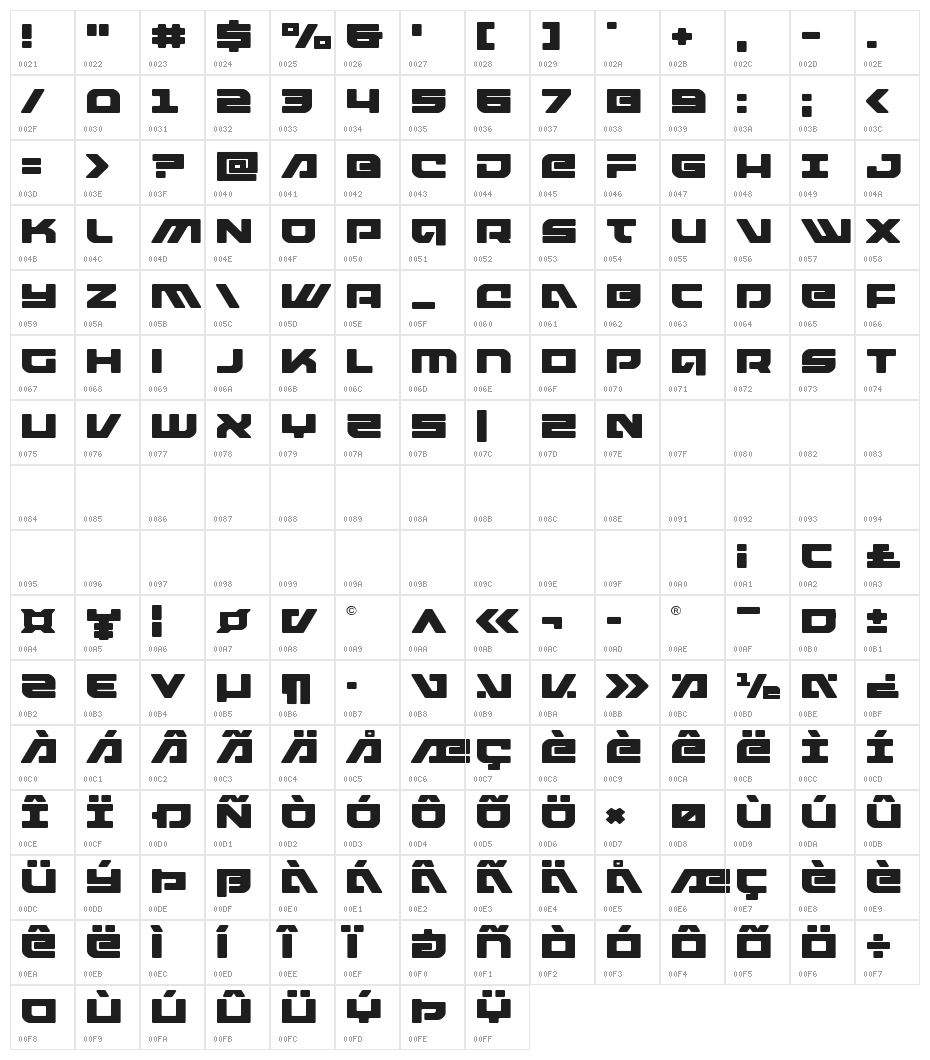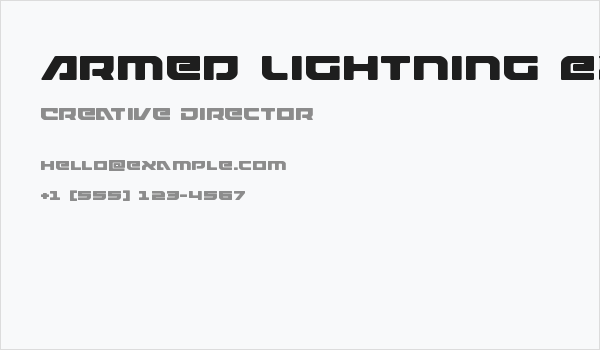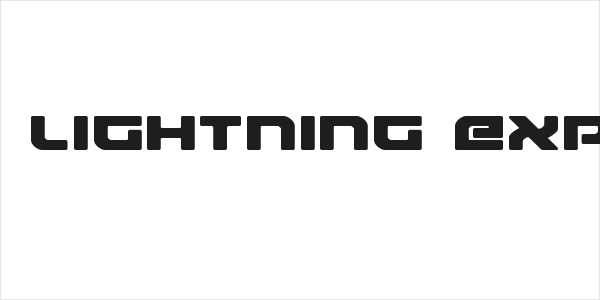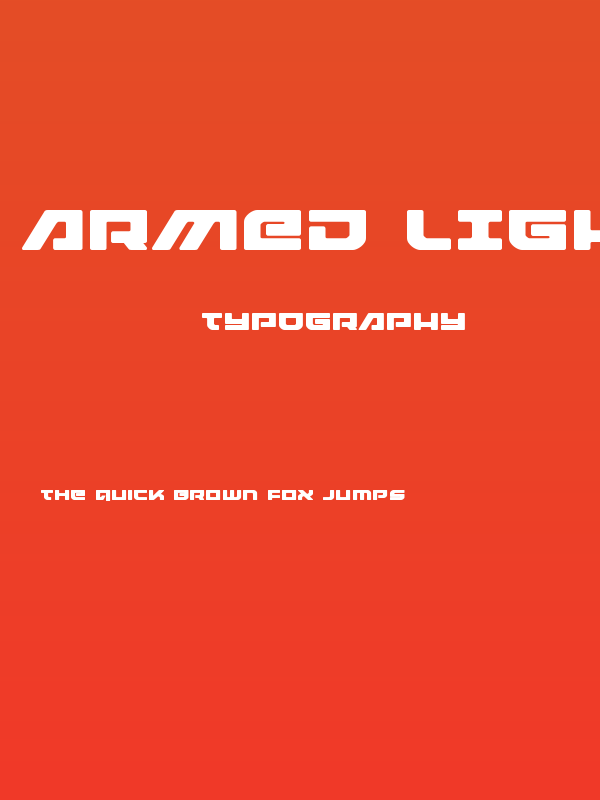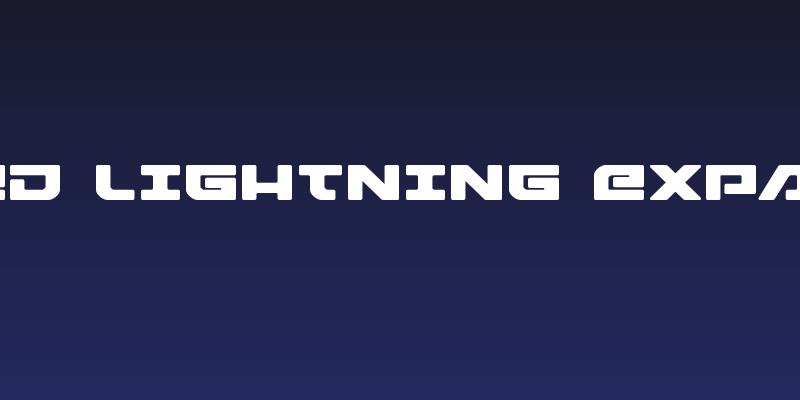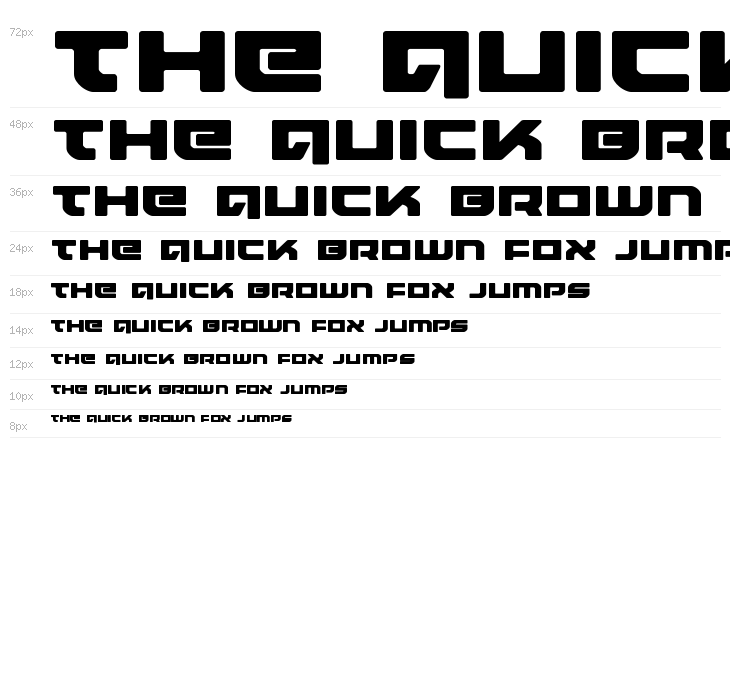
Armed Lightning Expanded Font
| Progetti proposti | Ideal for technology branding, sci-fi movie posters, video game titles, and modern advertising campaigns. |